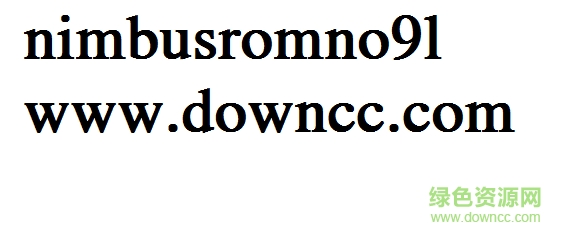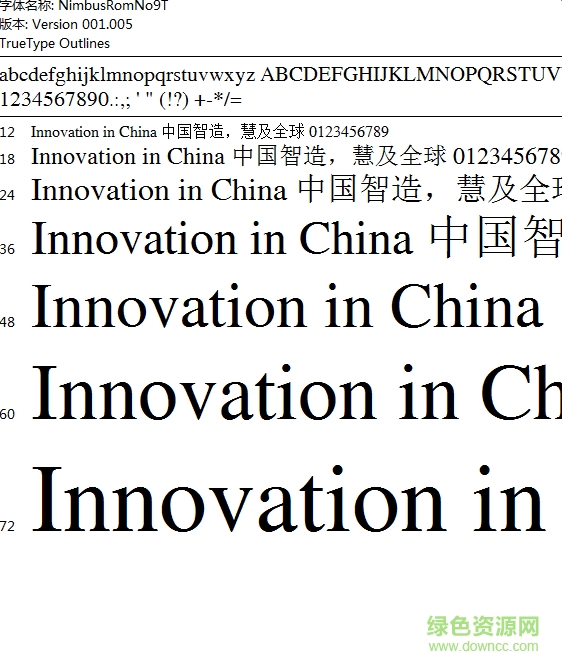
nimbusromno9l英文字體
nimbusromno9l字體是一款英文字體軟件,此字體筆畫(huà)一絲不茍,十分有韻味,可用于海報(bào)漫畫(huà)設(shè)計(jì)應(yīng)用,整體效果十分好看,喜歡的朋友歡迎到綠色資源網(wǎng)下載體驗(yàn)!
nimbusromno英文字體介紹
nimbusromno9l字體
nimbusromno9l字體筆畫(huà)不拘一格,給人清新脫俗的感覺(jué),十分好看迷人,綠色資源網(wǎng)為您提供綠色免費(fèi)的nimbusromno9l字體下載!